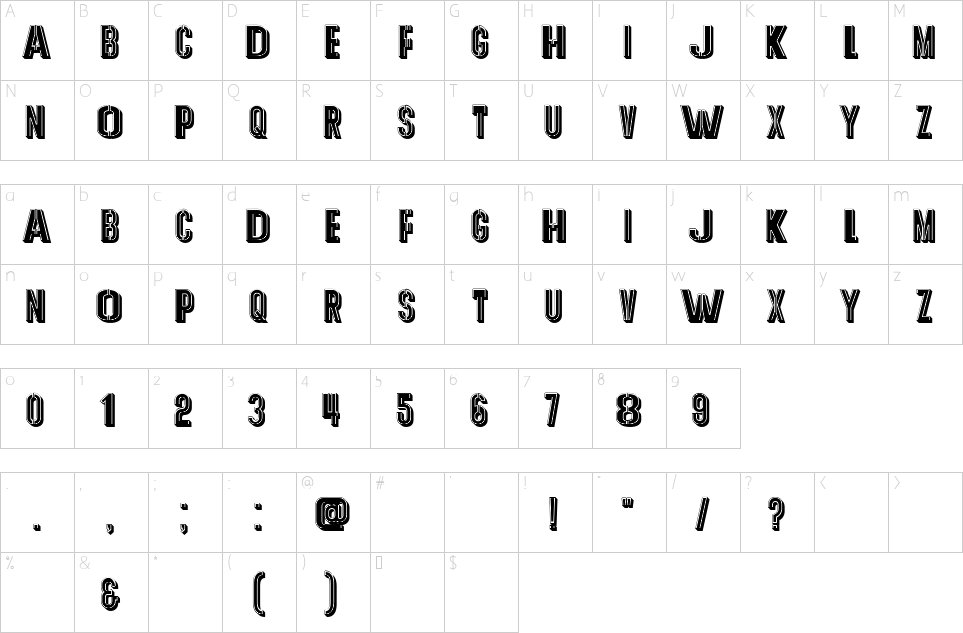
Descubra uma fonte original e diferenciada chamada Army Watch, especialmente criada para atender aos amantes de uma tipografia com um aspecto militar, moderno e sofisticado. Essa fonte foi projetada por Vladimir Nikolic e tem um design que reflete essa mistura única de força e elegância. Download a versão gratuita de Army Watch para Windows e Mac, disponível para quem busca uma fonte diferenciada para seus projetos gráficos. Com um design limpo e uma tipografia forte, Army Watch é uma escolha ótima para criar mensagens modernas e comunicativas. Seja para projetos de web, gráficos de design editorial ou até mesmo para criar um logotipo único, Army Watch está aqui para tornar sua produção visual mais atraente. Sua fonte agora está disponível gratuitamente e está esperando para enriquecer seu trabalho.